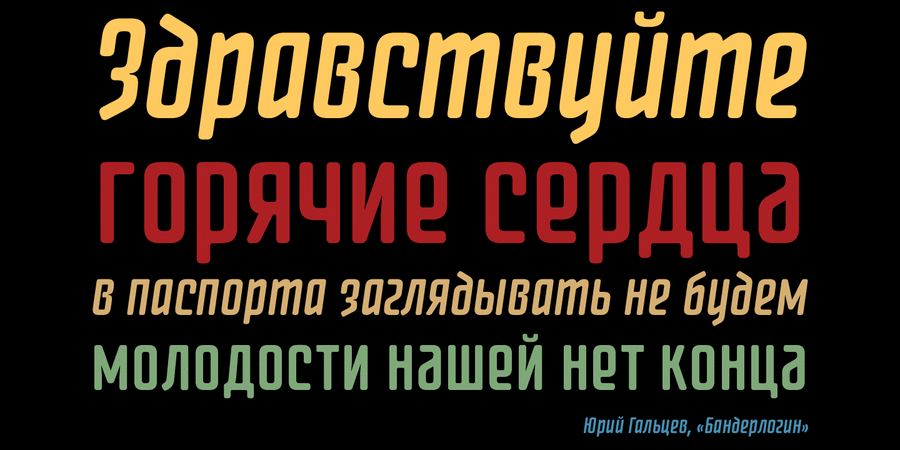
Шрифт Фонтатика сочетает технологичность с уютностью. Хорошо подходит для заголовков, плакатов и вывесок. Разработан Сергеем Ткаченко в 2012 году.
Особливості сімейства шрифтів Fontatica 4FХіт десятиліття:
Асоціації з сімейством шрифтів Fontatica 4FОсобистість і характер гарнітури:
прямий, техногенний, сильний, серйозний, переконливий, статичний, залізний, надійний, мужній, впевнений, сталевий, стабільний, рівний, автоматичний, стійкий, інженерний, точний, прямокутний, індустріальний, економний, міський, гладенький, високий, урбаністичний, комп'ютерний, експериментальний, крутий, футуристичний, неоновий, гумовий, кінематографічний, доброзичливий, приємний, динамічний